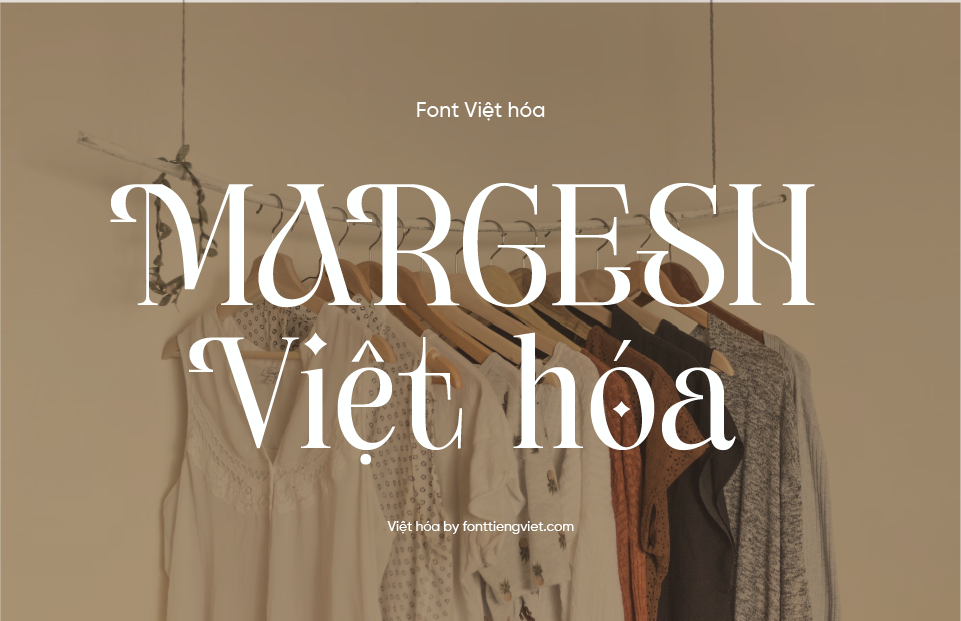
Font Việt hóa 1FTV VIP Margesh
Font Việt hóa 1FTV VIP Margesh – Bộ Font Chữ Sang Trọng Cho Thiết Kế Chuyên Nghiệp
Giới thiệu về Font Việt hóa 1FTV VIP Margesh
Trong thế giới thiết kế đồ họa hiện đại, việc lựa chọn một bộ Font Miễn Phí chất lượng luôn là ưu tiên hàng đầu của các nhà sáng tạo. Font Việt hóa 1FTV VIP Margesh nổi lên như một hiện tượng nhờ sự kết hợp hoàn hảo giữa nét cổ điển và hơi thở đương đại. Đây là một bộ font chữ Serif (có chân) mang phong cách sang trọng, tinh tế, đặc biệt phù hợp cho các dự án yêu cầu tính thẩm mỹ cao và sự chuyên nghiệp tuyệt đối. Với các đường nét được trau chuốt tỉ mỉ, bộ font này giúp nội dung của bạn trở nên nổi bật và thu hút thị giác ngay từ cái nhìn đầu tiên.
Đặc điểm nổi bật của Font Việt hóa 1FTV VIP Margesh
Thiết kế tinh xảo và đẳng cấp
Font Việt hóa 1FTV VIP Margesh sở hữu cấu trúc các chữ cái vô cùng cân đối. Điểm nhấn của bộ font này nằm ở các nét thanh nét đậm được xử lý mượt mà, tạo cảm giác thanh thoát nhưng vẫn đầy quyền lực. Đối với những bạn học sinh hay thầy cô giáo đang tìm kiếm sự mới mẻ cho các bài thuyết trình, Margesh sẽ là lựa chọn không thể bỏ qua để nâng tầm giá trị hình ảnh cho từng trang slide.
Khả năng hiển thị tiếng Việt hoàn hảo
Một trong những vấn đề lớn nhất khi sử dụng font ngoại nhập là lỗi font khi gõ tiếng Việt. Tuy nhiên, với phiên bản Font Việt hóa 1FTV VIP Margesh, mọi dấu câu và ký tự đặc biệt đều được tối ưu hóa 100%. Các nhà thiết kế tại Việt Nam đã dành nhiều tâm huyết để tinh chỉnh các dấu thanh sao cho hài hòa với độ cao của chữ cái, đảm bảo văn bản luôn mạch lạc và dễ đọc trên mọi thiết bị từ máy tính đến điện thoại di động.
Ứng dụng thực tế của Font Việt hóa 1FTV VIP Margesh
Thiết kế thương hiệu và bao bì
Nhờ vẻ ngoài mang tính biểu tượng, bộ font này thường được ứng dụng trong thiết kế logo cho các thương hiệu thời trang, mỹ phẩm hoặc trang sức cao cấp. Font Việt hóa 1FTV VIP Margesh giúp truyền tải thông điệp về sự uy tín và chất lượng. Khi kết hợp với những tông màu trung tính như vàng kim, trắng hoặc đen, bộ font sẽ phát huy tối đa sức mạnh thị giác của mình.
Sáng tạo nội dung trên mạng xã hội
Nếu bạn là một Content Creator, việc sử dụng Font Việt hóa 1FTV VIP Margesh cho các tiêu đề ảnh bìa Facebook, Instagram hay thumbnail YouTube sẽ tạo nên một dấu ấn riêng biệt. Sự độc đáo của Margesh giúp nội dung của bạn thoát khỏi sự rập khuôn của những bộ font hệ thống nhàm chán, từ đó tăng tỷ lệ tương tác và thu hút sự chú ý của người xem một cách tự nhiên nhất.
Lợi ích khi sử dụng Font Việt hóa 1FTV VIP Margesh
Kết luận về bộ Font Việt hóa 1FTV VIP Margesh